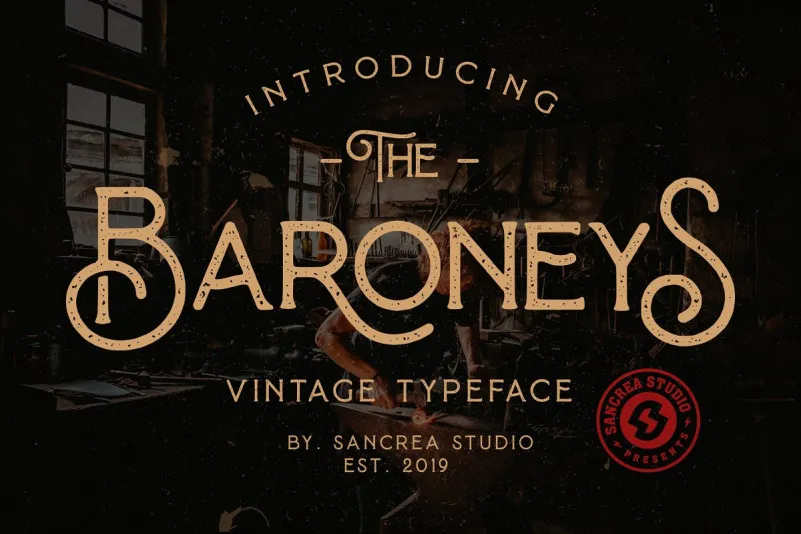
Baroneys Vintage Font – Download Grátis
A Baroneys Vintage Font é uma opção perfeita para quem busca um toque vintage sofisticado em seus projetos digitais e impressos. Introduzida pela 24Design, essa fonte serif vintage oferece um estilo único com sua forte contrastes de espessura e terminal ball distintivo que acrescenta um elemento de descontração a qualquer projeto. A Baroneys vem embalada para trabalhos criativos como arte digital, letras modernas em encaixetas de correspondência ou até mesmo design de livros e postagem. É perfeitamente adequada também para projetos de marca, design de artesanato ou até mesmo projetos que buscam um toque vintage pop e descompromissado. A fonte é texturizada e sua simplicidade elegante torna-a uma escolha atraente e versátil para diversos tipos de projetos que exigem um ar de sofisticação vintage.